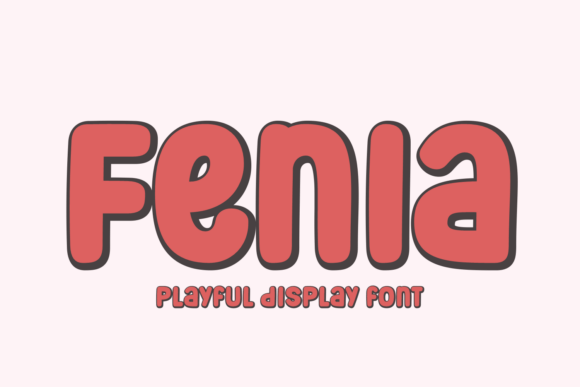
Fenia
適切なデザイン要素を見つけるのは難しい場合がありますが、Feniaは作品を即座に引き立てる優れたコレクションを提供します。
精密に作られたFeniaは、クリーンなベクター、滑らかなタイポグラフィ、そして安心のための商用ライセンスを提供します。
POD(オンデマンド印刷)製品、結婚式の招待状、またはソーシャルメディアのグラフィックを作成している場合でも、Feniaは理想的です。